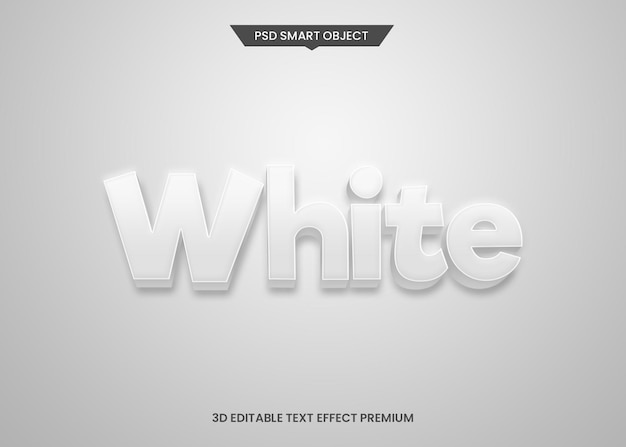
Стиль шрифта с эффектом редактируемого текста с тиснением белого цветаСтиль шрифта с эффектом редактируемого текста с тиснением белого цвета
Стиль шрифта с эффектом редактируемого текста с тиснением белого цвета